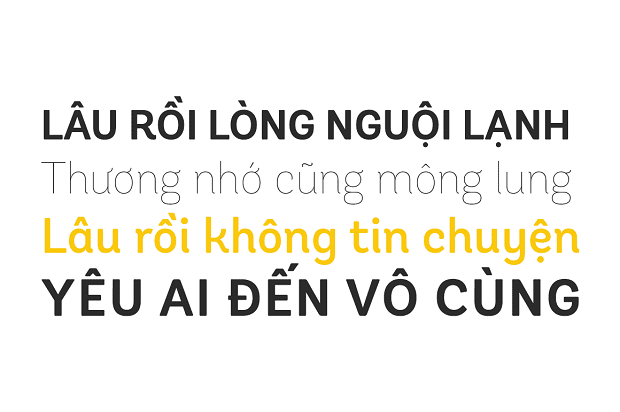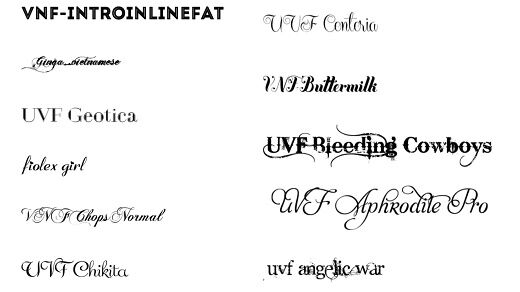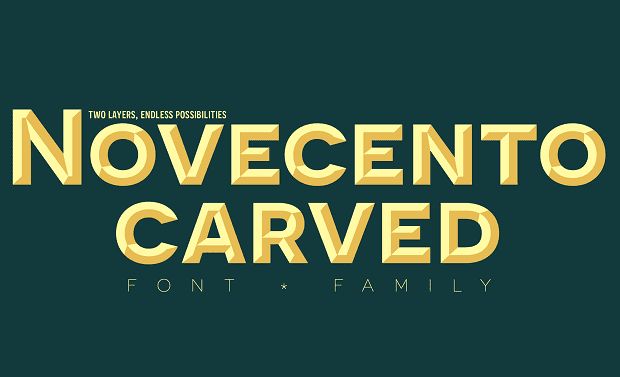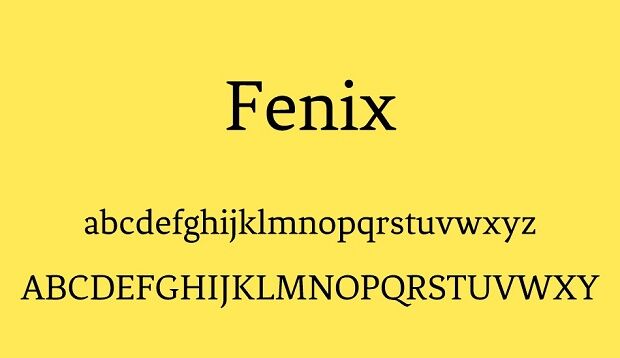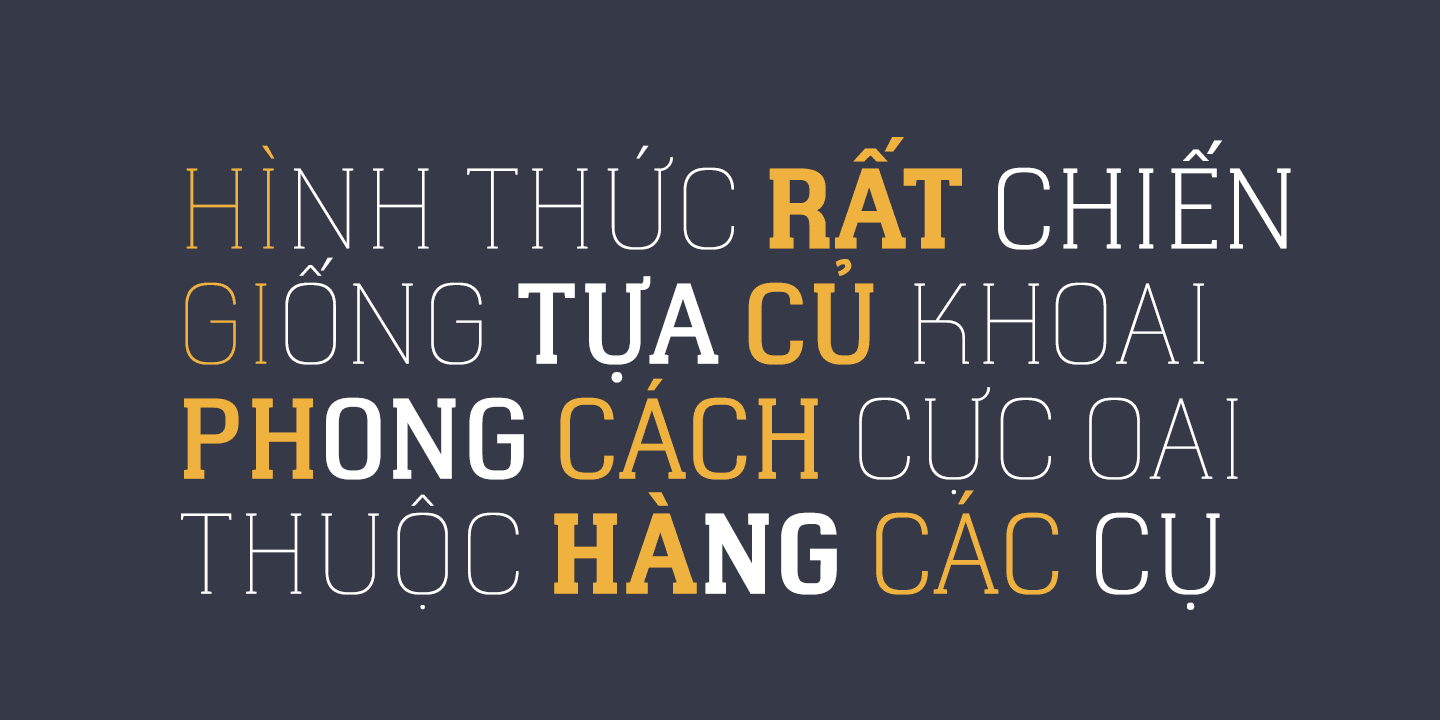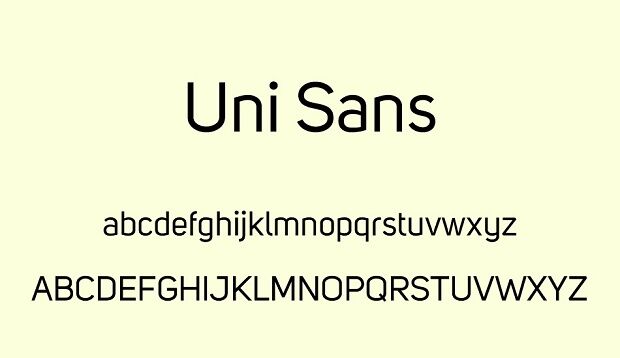
Các Designer Việt thường luôn gặp các vấn đề khi muốn sử dụng các Font chữ đẹp vì thông thường chúng sẽ không hỗ trợ các ký tự có dấu của Tiếng Việt (Unicode).
Giải pháp để sử dụng các font chữ này đó là bạn cần phải bỏ công tạo lại các dấu, ký tự bị lỗi, việc này khá mất thời gian và công sức.
Thật may mắn là ngày nay đã có khá nhiều người Việt Hoá lại font yêu thích và đã chia sẻ tại các diễn đàn, blog. Trong bài viết này, toonies sẽ tổng hợp lại các bộ font việt hoá mà bạn có thể tải về và sử dụng được ngay.
Tầm Quan Trọng Của Font Chữ Việt Hóa
Đối với ngành thiết kế, bên cạnh những yếu tố như màu sắc, hình ảnh, việc sử dụng Font chữ hợp lý, mỹ thuật được xem là một trong những yếu tố quan trọng nhất. Đặc biệt khi mà Digital Marketing phát triển. Các Font chữ xuất hiện trên Banner, Logo… đều có những tác động không hề nhỏ tới nhận thức của khách hàng
Các Font chữ đẹp ở tiếng anh rất nhiều, tuy nhiên, kho Font chữ Việt Hóa đẹp thì không được chia sẻ nhiều, hoặc nếu có cũng hoặc không tải được, hoặc sử dụng bị lỗi. Trong bộ Font chữ Việt Hóa được chúng tôi chia sẻ dưới đây sẽ có không ít những Font chữ mất phí. Chúng tôi chia sẻ không vì mục đích lợi nhuận.
Một số bộ Font chữ Việt Hóa
Bộ Font chữ TMF Việt Hóa
Đầu tiên, không thể không nói đến đó là bộ font chữ kinh điển mà mọi Designer đều nên cài đặt trong máy tính của mình. Bộ font có khả năng tương thích với rất nhiều phần mềm gõ tiếng việt thông dụng hiện nay như Unikey, Vietkey…. Bộ Font vô cùng đồ sộ với rất nhiều mẫu Font hiếm đã được chúng tôi dày công sưu tầm đầy đủ.
Với gần 400 Font tổng cộng, đầy đủ các thể loại từ đậm, nhạt, cho tới các Font chữ nghệ thuật như thư pháp, không quá khó hiểu khi nói rằng đây là bộ Font chữ Việt hóa mà mọi anh em thiết kế đều nên có sẵn
Font Việt hóa phong cách serif
Với những nét chữ có chân, mang phong cách cổ điển. Font chữ Serif được sử dụng rất thường xuyên trong các ngành thiết kế thời trang hoặc in ấn để làm nổi bật lên sự sang trọng hoặc cổ điển đặc trưng mà font chữ việt hóa này mang lại
Với những font Việt hóa mang phong cách serif không quá cầu kỳ, phức tạp, tuy nhiên cũng chính bởi sự đơn giản đó lại được rất nhiều người yêu thích sử dụng để thiết kế. Sau đây là một số Font chữ Việt Hóa với phong cách Serif mà chúng tôi đã tuyển chọn
Font Cambria
Thanh lịch duyên dáng với nét chân chữ rõ ràng. Nếu muốn thể hiện một đoạn văn bản nghiêm túc, trang trọng nhưng không muốn quá cứng nhắc với kiểu font Times News Romans thì Cambria là font việt hóa lựa chọn phù hợp nhất với bạn lúc này.
Font Travelling Typewriter
Ngay chính cái tên cũng đã thể hiện được “diện mạo” font chữ này. Nếu bạn là người bị thu hút bởi những nét chữ đánh máy ngày xưa, đơn điệu nhưng có chất riêng thì đây chính là font chữ bạn đang cần.
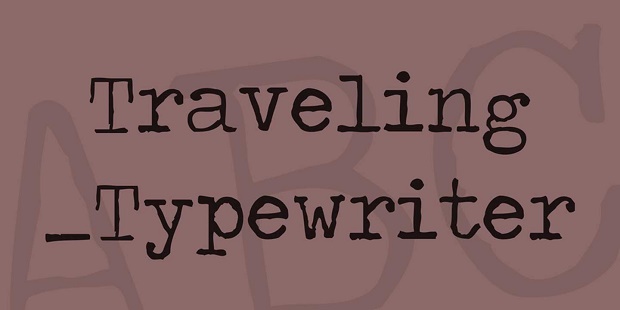
Cha đẻ của font chữ này, Fernando Díaz cho biết ông lấy cảm hứng từ chữ calligraphy (một dạng chữ viết tay từ bút lông và mực). Chính vì vậy mà chúng ta có thể thấy được sự kết hợp hài hòa giữa những đường gạch chân mạnh mẽ và các đường bo tròn mềm mại. Đối với những đoạn văn bản dài, bạn có thể sử dụng font Việt hóa này để tạo cảm giác hứng thú cho người đọc.
Được giới thiệu lần đầu tiên vào tháng 1 năm 2013, được lấy cảm hứng từ bóng chày và những ấn phẩm từ năm 1950. Bộ font việt hóa này bao gồm 6 kiểu từ Light cho đến Black, đã được việt hóa trọn bộ, kerning và opentype hoàn chỉnh.
Font Việt hóa phong cách Sans-Serif
Sans-Serif, đúng như tên gọi của mình, kiểu font việt hóa này không có gạch chân (serif) trong cấu trúc chữ. Sans-Serif được tạo ra sau Serif với những đường nét mới mẻ hơn. Nó thường được dùng cho những thương hiệu công nghệ bởi tính dứt khoát, rõ ràng. Bạn sẽ dễ dàng nhận thấy điều này khi nhìn vào các ứng dụng, trang web hay các nền tảng kỹ thuật số. Bởi điểm cộng lớn nhất của kiểu font này là rất dễ đọc trên giao diện điện thoại.
Dưới đây là 1 số font sans-serif Việt hóa phổ biến trong các thiết kế:
Font Uni Sans
Font chữ dùng được hầu hết trong tất cả các thiết kế: trang web, đồ họa, thời trang, poster, logo…Đặc biệt, nếu dùng font việt hóa này để thiết kế tựa đề thì chắc chắn bài viết của bạn sẽ tạo ấn tượng về mặt thẩm mỹ ngay.
Được đánh giá là sản phẩm hòa trộn giữa các trường phái typography. Font việt hóa này phù hợp với logo, tạp chí, sách báo…
Là một font việt hóa được sử dụng chủ yếu cho tiêu đề, thiết kế thương hiệu hoặc câu trích dẫn (quote). Các kiểu chữ mảnh của font việt hóa này làm cho thiết kế trông hiện đại và kiểu chữ in đậm thì lại mang đến cảm giác cổ điển hơn.
Với thiết kế độc đáo được lấy cảm hứng từ những bảng chỉ dẫn của vùng Bueno Aires, thường được dùng nhiều trong việc thiết kế tiêu đề dạng chữ to. Do không có kiểu Italic nên font chữ này không phù hợp với những đoạn văn bản dài. Font chữ này đã được tinh chỉnh ở cả giao diện máy tính và điện thoại.
Một font chữ mới được ra mắt, là sự kết hợp giữa các yếu tố typography, lettering handmade, swash cùng phong cách không chân gạch. Tuy mới, nhưng đã nhận được phản hồi rất tốt từ phía các anh em trong cộng đồng thiết kế, bạn có thể sử dụng để làm Banner, Poster, thiệp mời. Font việt hóa này giúp mang lại sự tinh tế, đơn giản, vừa hiện đại vừa cổ điển cho các thiết kế.
Kết luận